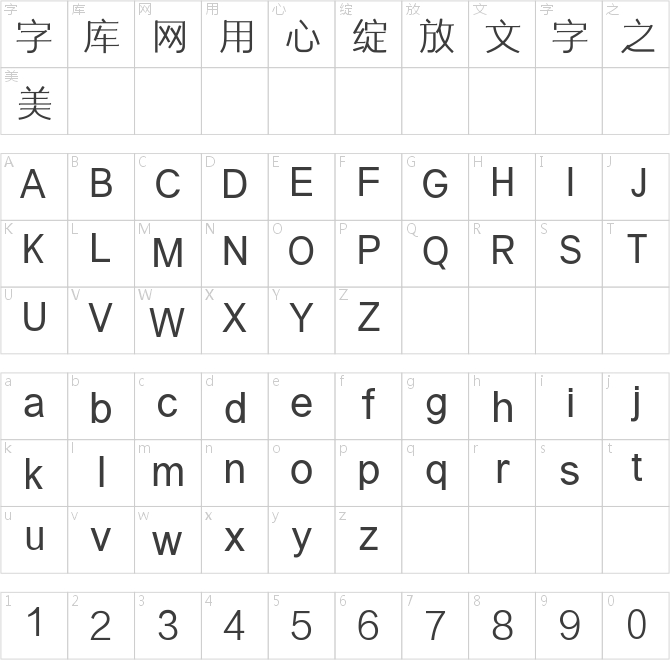
字体名称: 三极颂黑简体
三极颂黑简体
三极颂黑简体的颂用了跟宋的同音,此款字的横竖勾带有宋体结构,其字形清新,结构严谨,布白均匀,结合了宋体饱满的结构特征,又不失黑体本身的锐利简洁,精致且富有内涵。
三极颂黑简体字体SJsonghei字库是一款让人赏心悦目、百看不厌的中文字体,适合各类广告和产品包装设计应用,字体大小2.27MB,格式为ttf字体,上传用户是三极字库,作者/版权方为三极字库/夏桑霜